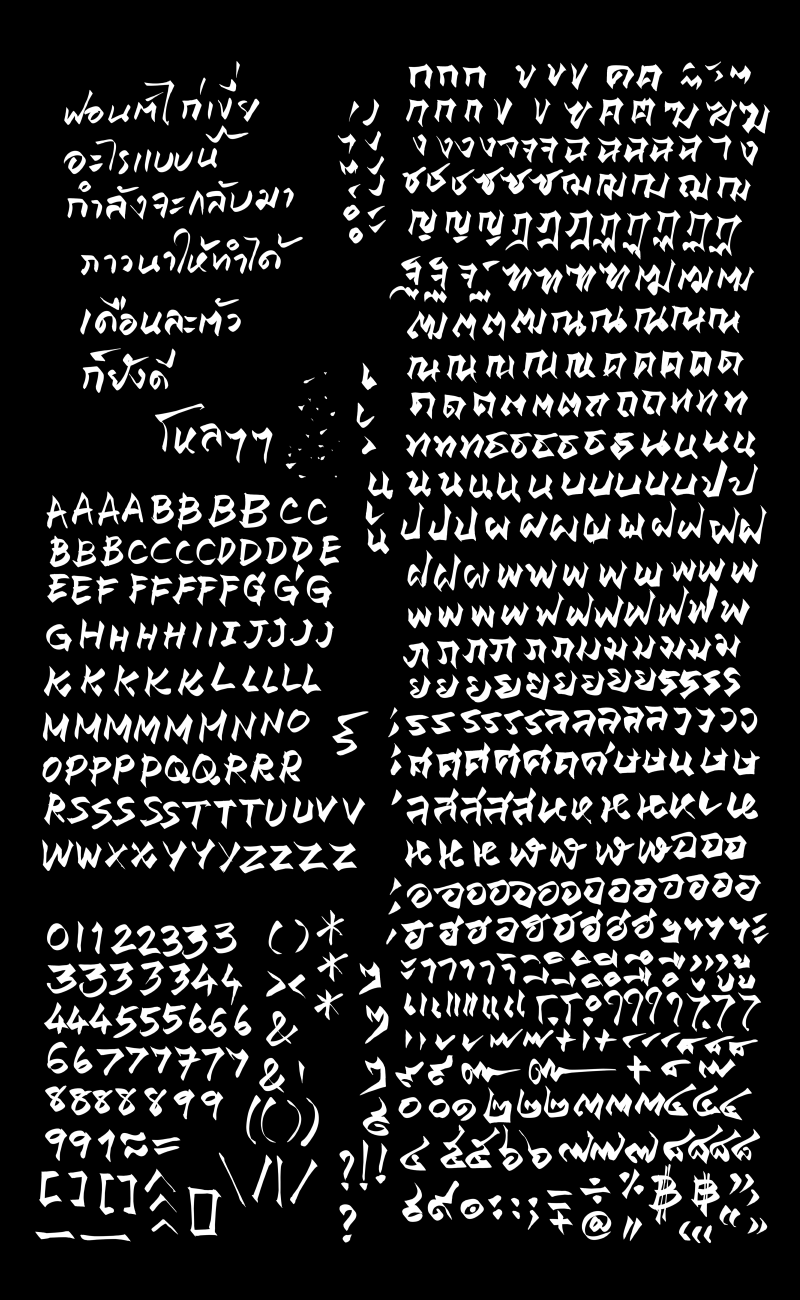
ฟอนต์ a chicken
ตั้งใจมากว่าปีนี้จะกลับมาทำฟอนต์ครับ หลังจากหายหัวไปหกเจ็ดปีแล้ว
แต่นี่มันล่อมาเดือนมีนาแล้ว ยังไม่ได้เริ่มทำเลย
เวลาว่างมีครับ ไม่ได้ยุ่งขนาดไม่ว่าง แต่ดันเอาเวลาว่างไปทำอย่างอื่นหมด
ต่อไปนี้เลยตั้งใจจะกลับมาทำฟอนต์เล่นเดือนละตัวครับ เน้นว่ายังทำเล่นๆ เหมือนเดิม
(เพราะไม่สามารถทุ่มเทให้ได้งานระดับเนี้ยบๆ ได้ :3005:)
อันนี้เป็นร่างแรกของ a chicken ที่เล็งๆ เอาไว้ว่าน่าจะมาแนวนี้แหละครับ
(มานั่งนึกดูว่าการตั้งชื่อฟอนต์นำหน้าว่า iannnnn มันเกะกะสายตามาก โดยเฉพาะเวลาทำพรีวิว
เลยรวบเหลือ a ตามด้วยชื่อสัตว์สิ่งของอะไรก็ว่าไป ง่ายดี :30:)
เขาจะทำฟอนต์เดือนละตัวได้อย่างที่ต้งใจหรือไม่ โปรดปล่อยผ่าน ไม่ต้องสนใจ
ป้าดดดดดหลงรักเลยครับจังหวะ อารมณ์ใช่เลย รอเลยครับ :35:
อารมณ์พู่กันหัวตัดมากๆ โคตรชอบ :25:
เริ่มเป็นตำนานตั้งกะปฏิสนธิเลยนะฟ้อนต์นี้ สะดุดรูขุมขนมากครับ  :43:
เดี๋ยวๆๆ ยังไม่ได้ทำอะไรเลยนะครับ :3005:
อย่าเพิ่งหมดไฟนะ  :30:
ทำไปทำมามันจะดูเหมือนฟอนต์พู่กันจีนขึ้นไปเรื่อยๆ แฮะ
ช่างมันเถอะ  ลองถ้าจะไหลก็ไหลไป :30:
สุดยอด แค่เลขสามก็มีแปดแบบแล้วววว
น่าเล่น opentype feature มาก  :30:
เห็นตูขยันแบบนั้นเลยเรอะ :59: